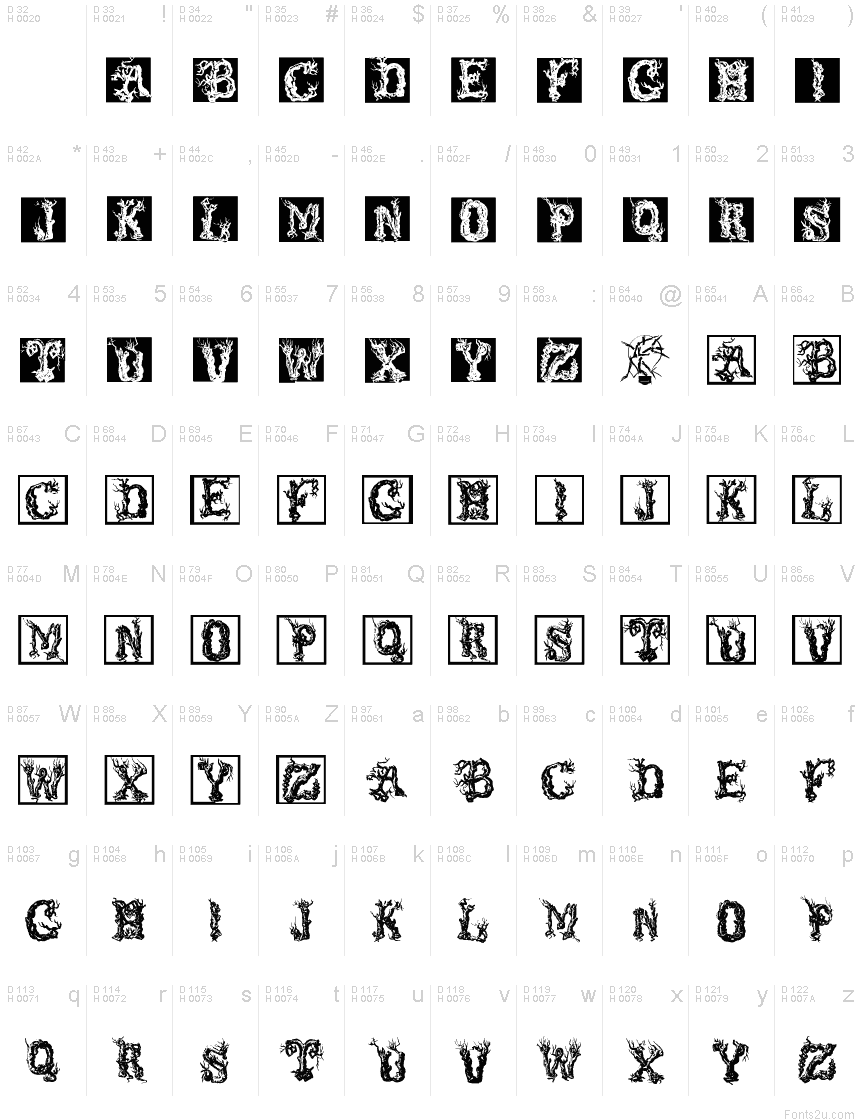
TreeLike di M. Klein è un carattere gratuito che evoca rami di bosco, con un tocco fantastico e nodoso. Le maiuscole sembrano essere cresciute naturalmente piuttosto che disegnate, con bordi ruvidi simili alla corteccia, rametti che si attorcigliano e forme nodose che rendono le lettere come piccoli pezzi di una foresta oscura.
È perfetta per poster, copertine di libri, volantini di Halloween, titoli di videogiochi e packaging a tema dove la grafica deve trasmettere l'atmosfera da sola. Trattandosi di un font gratuito, è ideale anche per titoli brevi, monogrammi e capilettera, poiché le forme a ramo intrecciato sono più efficaci quando lasci che alcune lettere agiscano come oggetti illustrati.
TreeLike